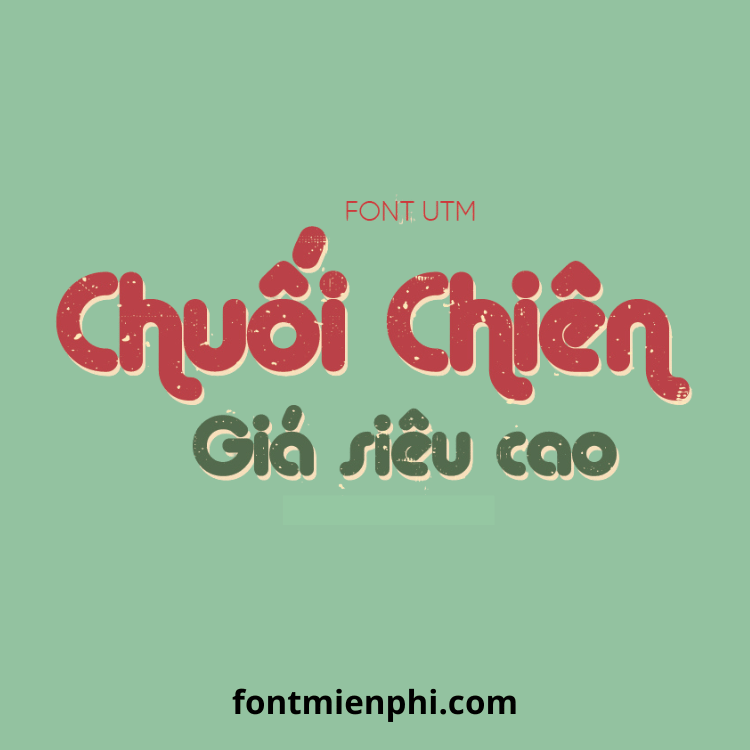
Việt hóa font UTM Alba Matter
Giới Thiệu Font UTM Alba Matter Việt Hóa
Font UTM Alba Matter là một trong những font chữ đẹp, hiện đại với nét thanh mảnh, phù hợp cho thiết kế logo, banner, in ấn và các dự án sáng tạo. Bản Việt hóa UTM Alba Matter trên Fontmienphi.com đã được tối ưu để hỗ trợ đầy đủ tiếng Việt, giúp người dùng sử dụng dễ dàng mà không lo lỗi font.
Đặc Điểm Nổi Bật Của Font UTM Alba Matter
• Hỗ trợ tiếng Việt đầy đủ (có dấu, đúng chuẩn Unicode).
• Phong cách hiện đại, phù hợp với thiết kế thời trang, quảng cáo.
• Đa dạng kiểu chữ (Regular, Bold, Italic…).